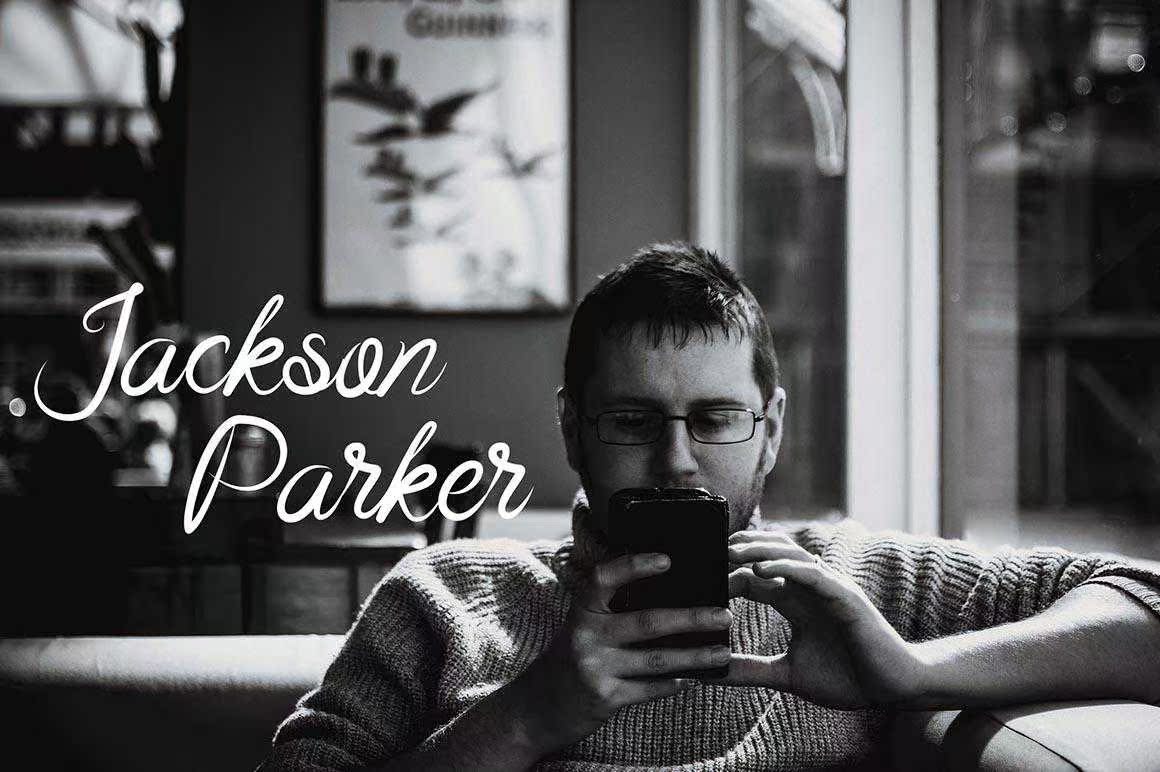
介绍Beast Fantasia,Astylish Handriten with Signature Style。此美丽的脚本字体以优雅、优雅和现代的外观为您的最新项目提供个性化触感。介绍Beast Fantasia,Astylish Handriten with Signature Style。此美丽的脚本字体以优雅、优雅和现代的外观为您的最新项目提供个性化触感。